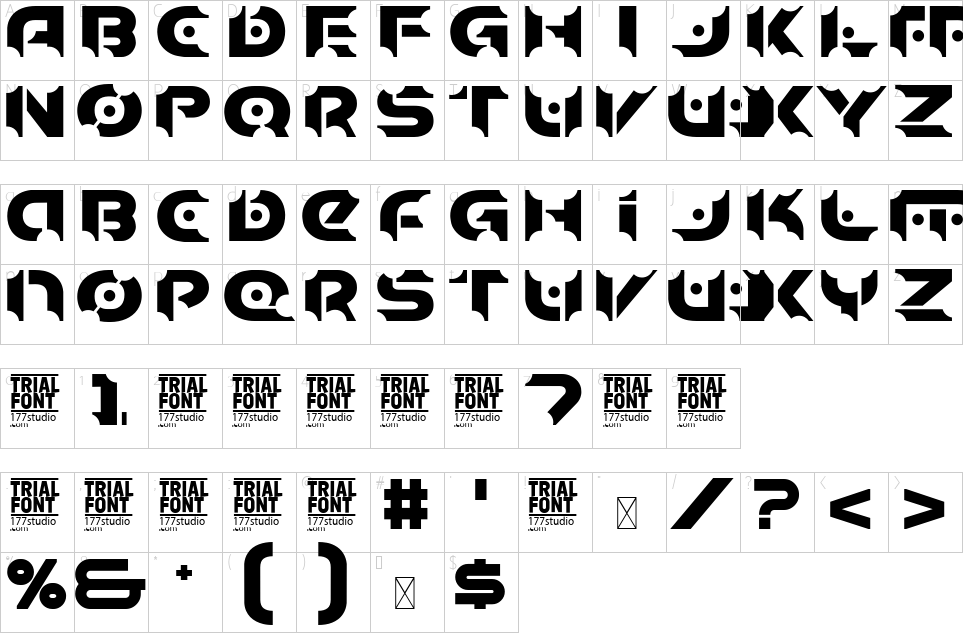
A fonte Justice Display é uma opção clara e elegante para qualquer projeto onde um estilo poderoso e moderno é desejado. Ela foi desenvolvida por 177Studio.com e, desde sua publicação, já foi baixada 1.631 vezes. Esta fonte ideal para design gráfico, impressão e publicidade, oferece um design limpo e fácil de ler que destaca a sua mensagem em ambientes visuais. O Justice Display vem em uma família com vários tamanhos e opções de estilo, o que significa que você pode adaptá-la facilmente para o seu projeto. Seja você um designer de logotipos, um gráfico ou um editor de fotos, a Justice Display pode ser a fonte perfeita para destacar seu trabalho.